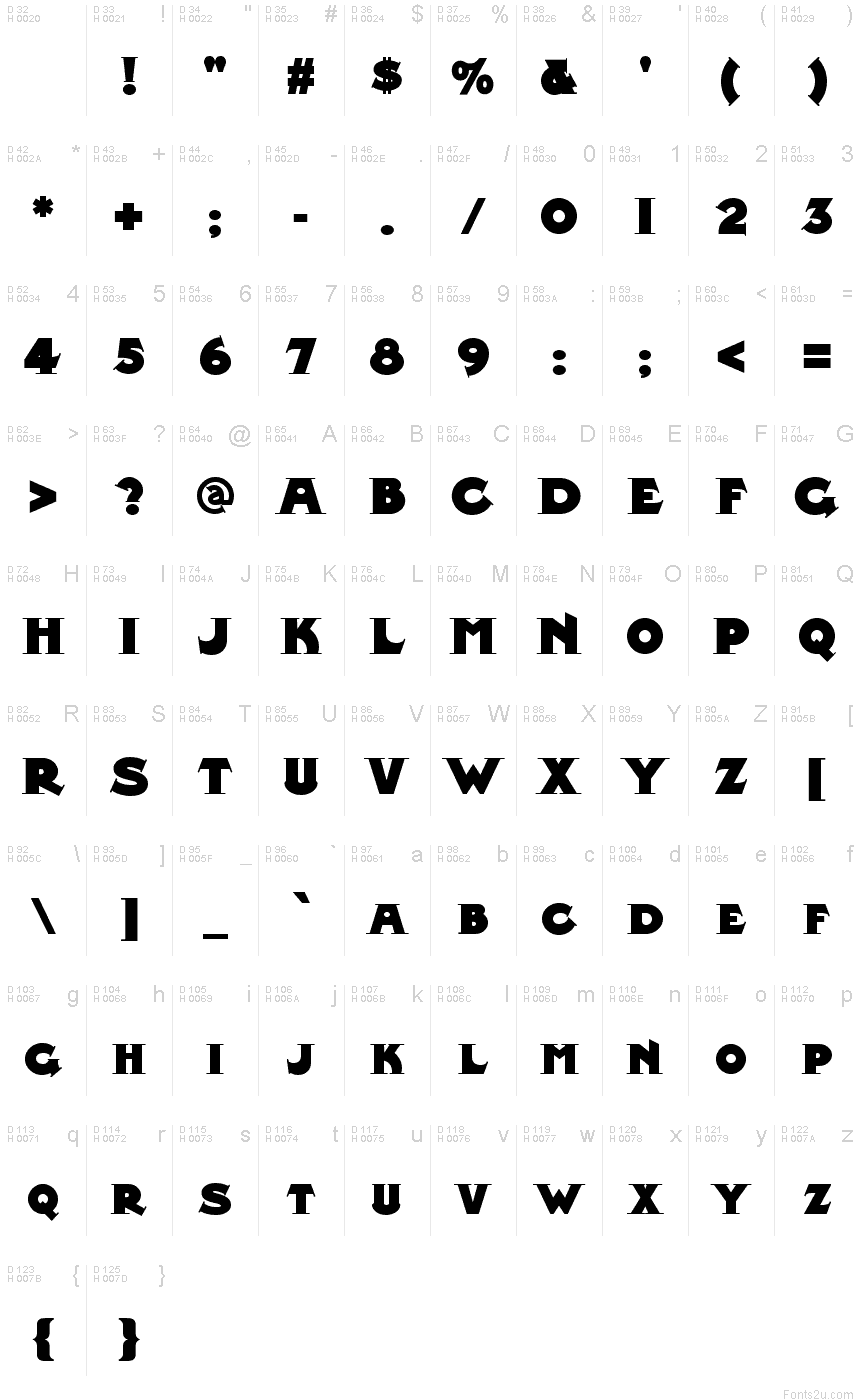
MidlandRailNF
Midland Rail NF autorstwa Nicka Curtisa to darmowy, utrzymany w stylu retro font, inspirowany sylwetką kolejowych znaków i kwadratowymi, blokowymi formami. Kształty liter łączą proste linie z zaokrąglonymi wycięciami, co przywodzi na myśl malowane metalowe napisy ze stacyjnych tablic. Midland Rail NF idealnie sprawdzi się w plakatach vintage, szyldach, logotypach, projektach opakowań i menu w stylu diner, które potrzebują wyrazistego klimatu dawnych lat. Szerokie liternictwo i wyraziste krzywizny świetnie nadają się także do krótkich nagłówków, plansz tytułowych oraz grafik eventowych, gdzie typografia stanowi główny element designu bez zbędnych ozdobników.